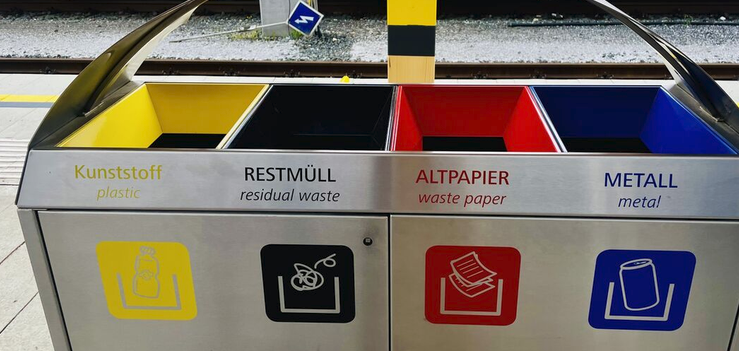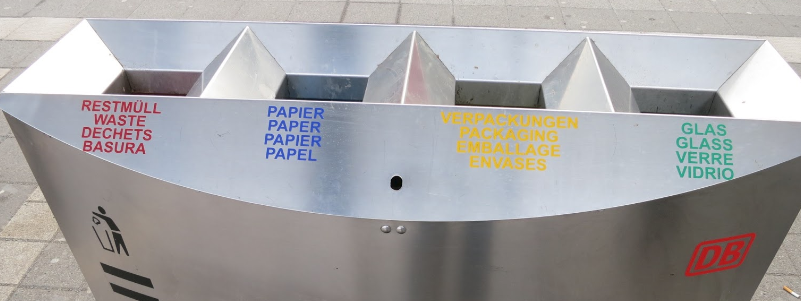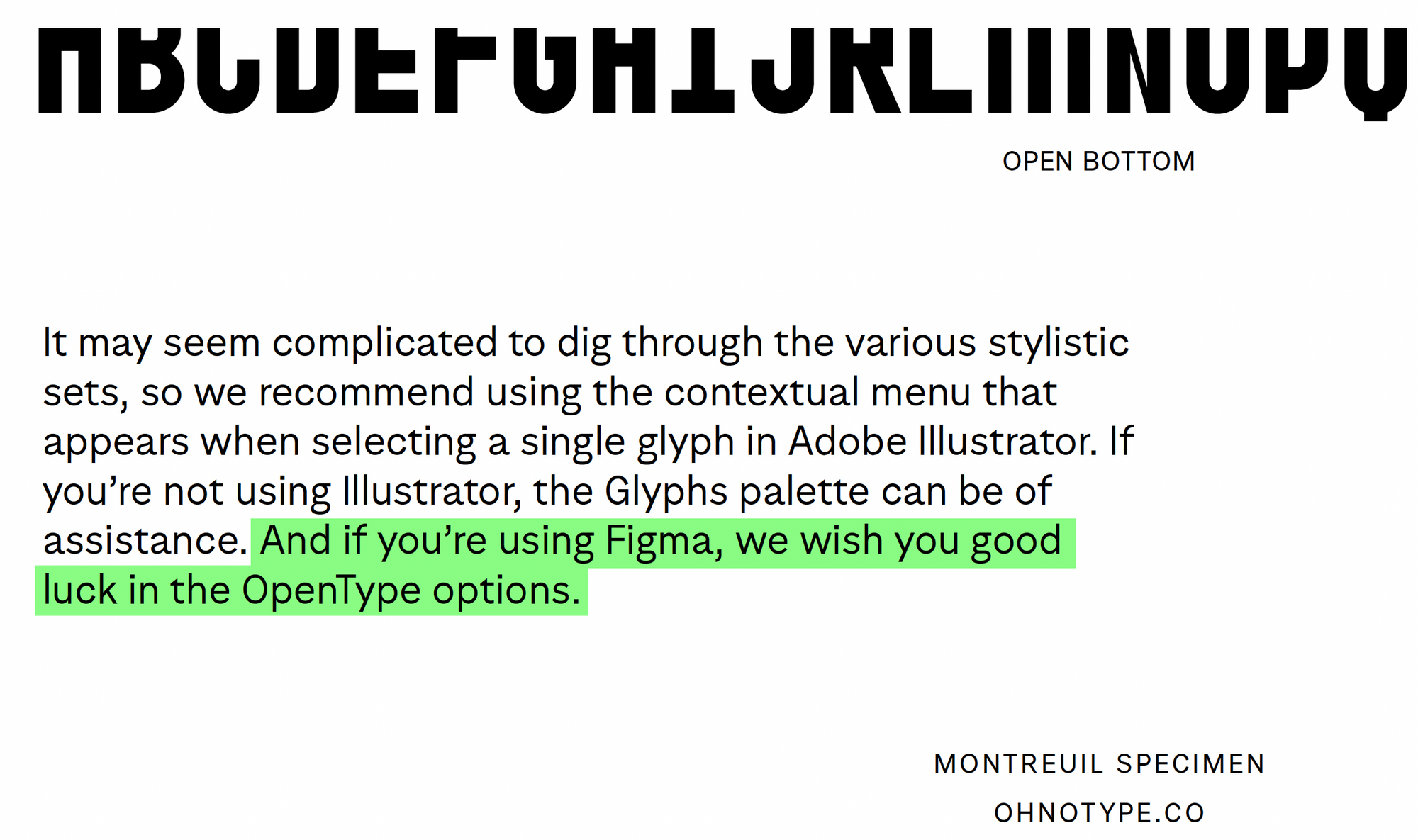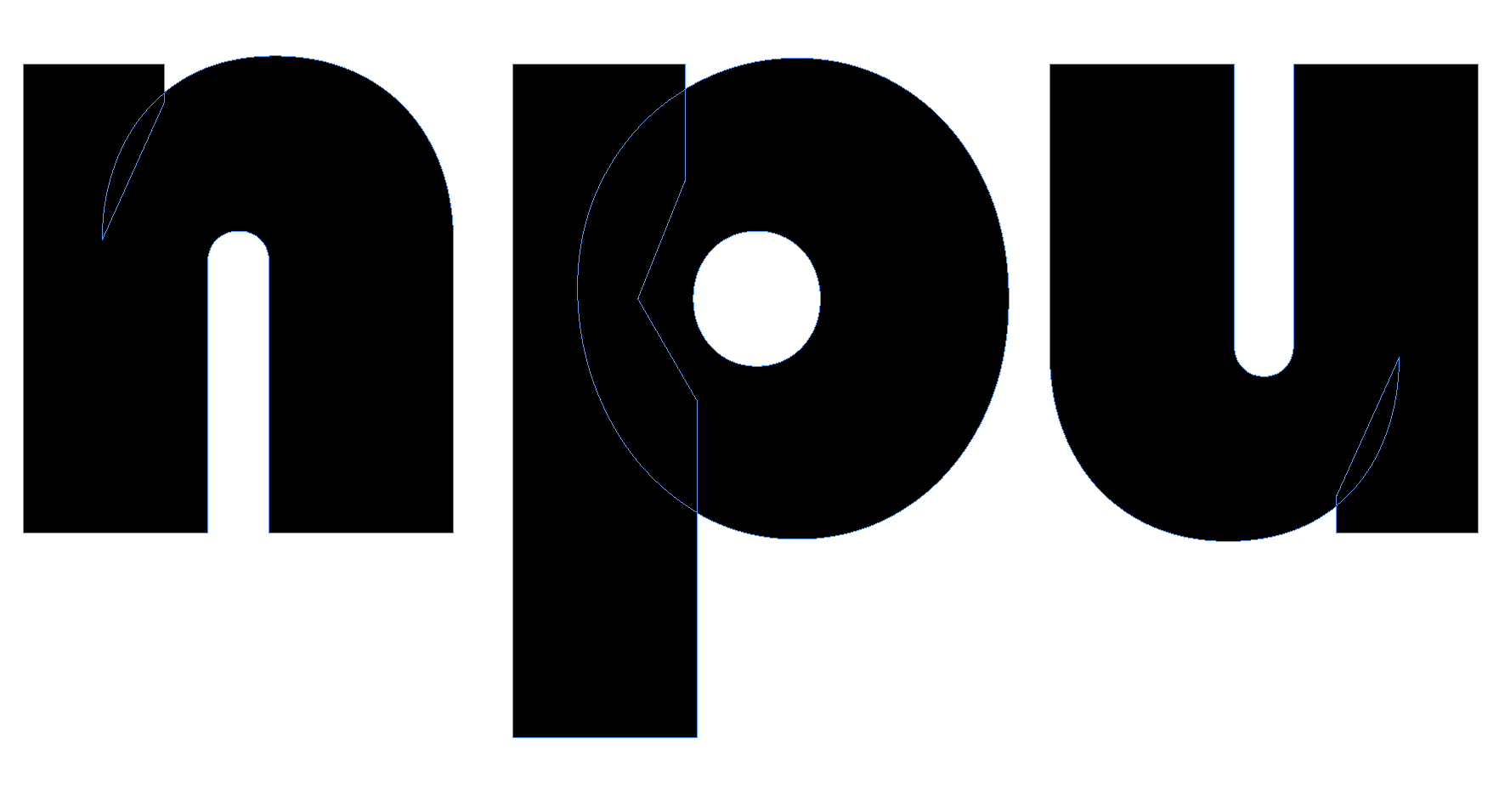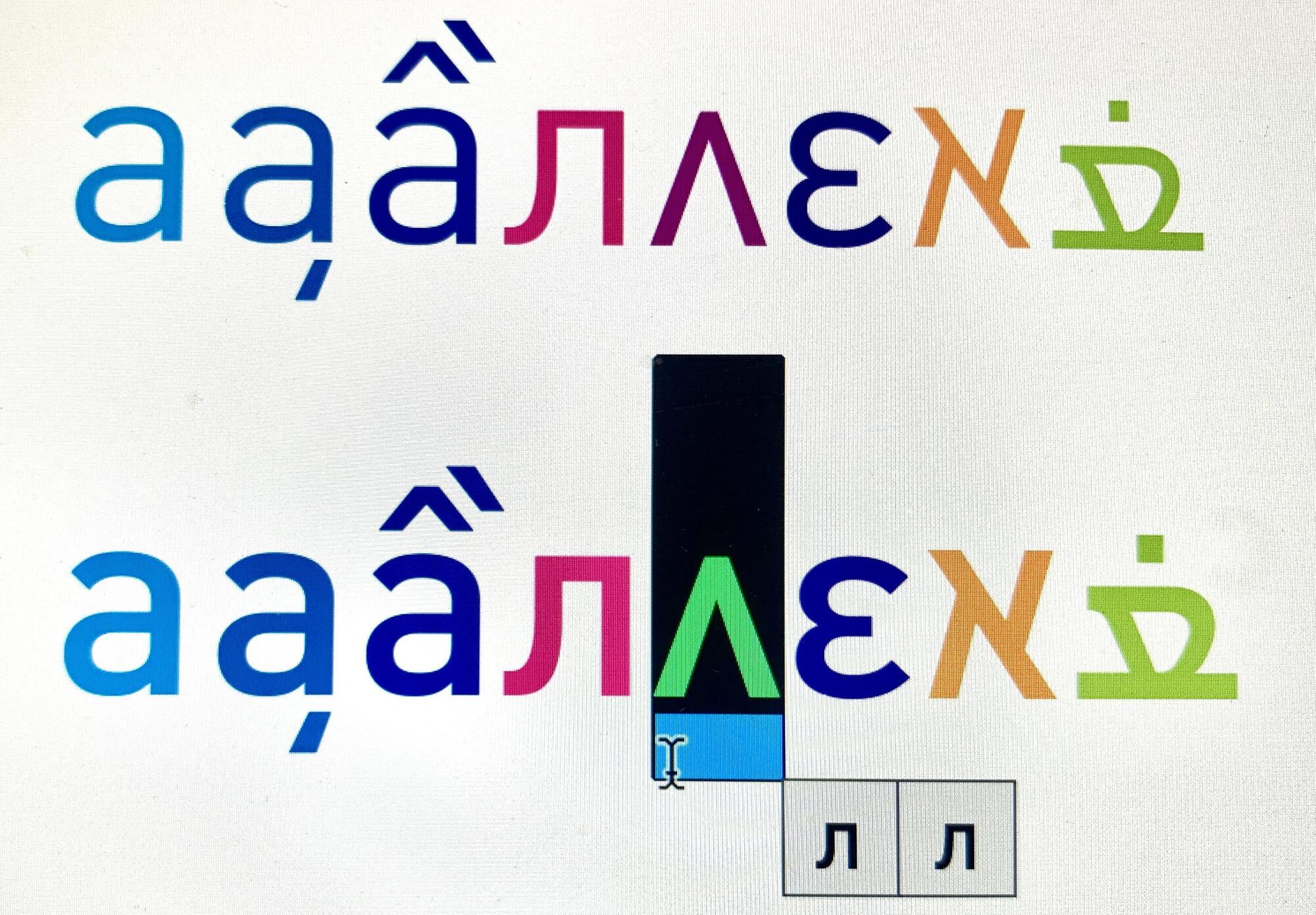
"Freigabesack"
Noch nie davon gehört.
Eventuell doch eher »Fehlwurf« (steht anscheinend für Fremdstoffe/Fremdgut). Also Material, das falsch entsorgt wurde(?).
Ich werfe noch »Food« ins Rennen. Also für mit Essen kontaminierten Müll bzw. einfach nur Reste. In Hamburg gibt es für Restaurants dafür eine eigene Mülltonne.
In Hamburg ist auf diesen Säcken eine Menge Zeug draufgedruckt, kann man bei Budni kaufen (https://www.budni.de/sortiment/produkte/4072612004). Dazu gibt es noch Spezialsäcke von der Stadtreinigung für Häuser, die keine Tonnen/Container haben können. Die sind auch gekennzeichnet, damit die von der Stadtreinigung mitgenommen werden und die nicht die Mülldetektive losschicken, um zu gucken, wer da einfach seinen Müll entsorgt hat. Die gibt es in unterschiedlichen Farben, momentan sind sie rosa: https://www.eimsbuetteler-nachrichten.de/rosa-muellsaecke-hamburg-eimsbuettel/
Danke, mir war nur der Begriff »Freigabesack« nicht geläufig. Aber diese Spezial- bzw. Zusatzsäcke ergeben für den privaten Haushalt Sinn, aber eher weniger für den Hauptbahnhof. Sie wirken irgendwie inhouse, kann mich aber auch irren …
Denke ich auch, irgendein internes Mülltrennungssystem.
Theoretisch trennt die Bahn den Müll, in Hamburg ist da aber nur ein Sack (vielleicht zwei) drin:
Wenn die Farben auch den Säcken entsprechen und die Bahn in München trennt, dann könnte das ein Restmüllsack sein.
Oder ein mitgereister Sack aus Österreich?
Nein, mir sind die schon ein paar Mal aufgefallen …
Da fällt mir wieder auf, dass es nach wie vor kein Kontext-Menü in InDesign und Illustrator gibt, das den Zugriff auf Zeichenvarianten (CVxx) ermöglicht. Figma hat das schon lange implementiert. -(
Mir geht es um die Thematik, die hier schon mal behandelt wurde:
Für einzelne Wörter kann man das händisch so handhaben. Es gibt aber meines Wissens keine Möglichkeit in InDesign/Illustrator, einzelne Zeichenvarianten von Glyphen global einzustellen (analog zu Stylistic Sets).
Ich habe gerade einen Font in Pfanne umgewandelt um etwas anzupassen und so sehen die Pfade aus. Ist das üblich? aschehaupt
Wenn es eine variable Schrift ist, ja. Sowas verbessert die Interpolation zwischen Mastern. Früher hat man sowas vor der Generierung der statischen Schriften rausgerechnet, heute bleibt es bei variablen Schriften notgedrungen drin.